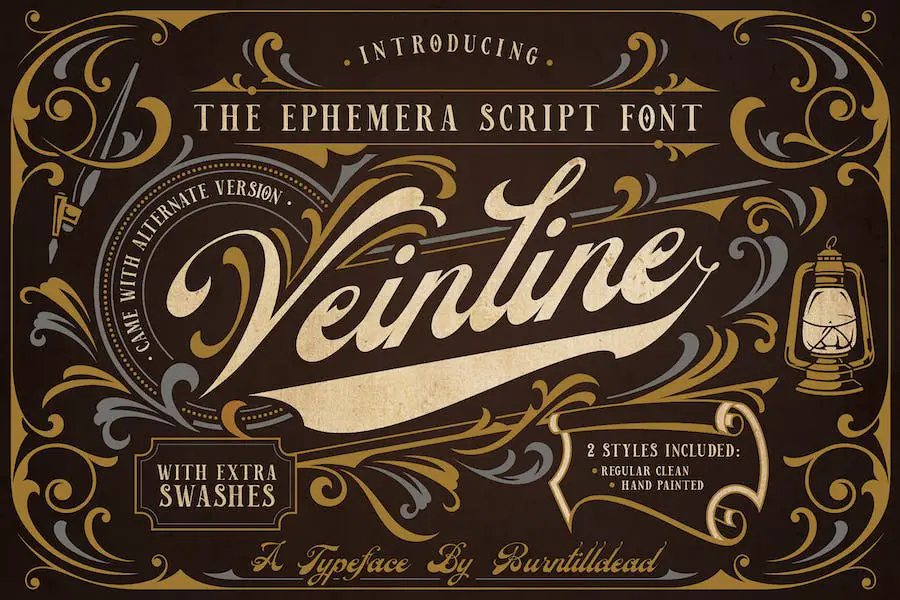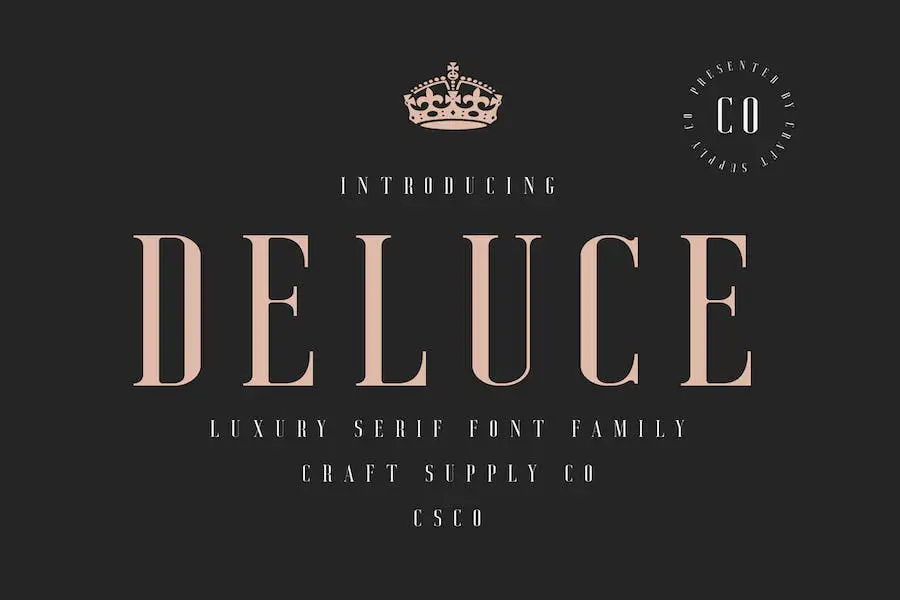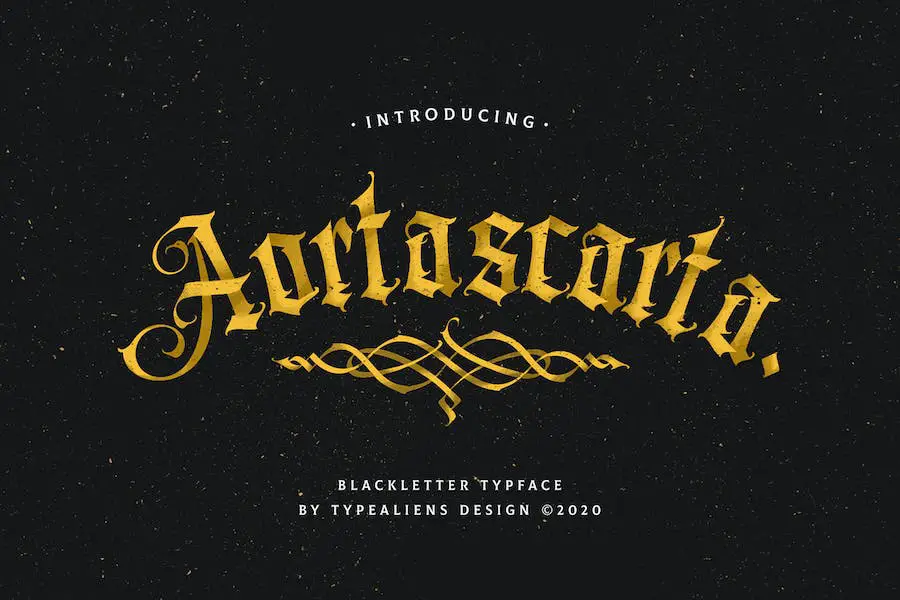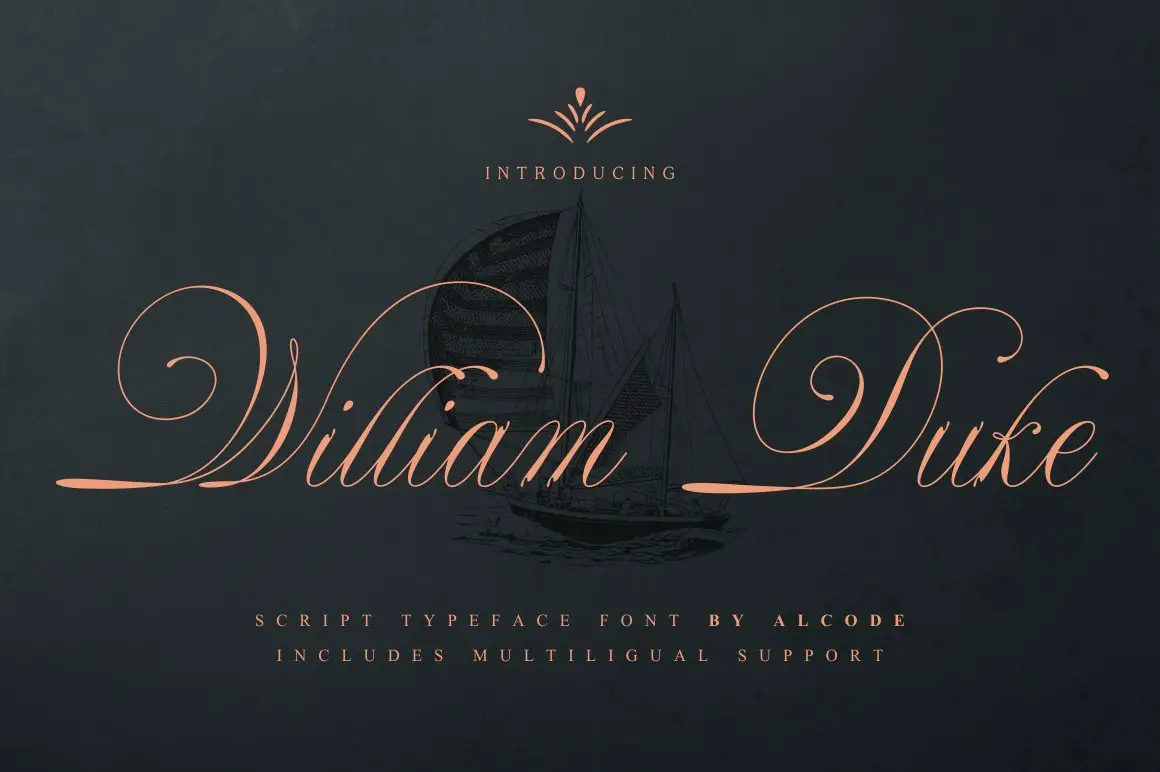
20 meilleures polices de certificat 2023 (gratuites et premium)
Publié: 2023-03-26La meilleure police pour votre certificat peut le faire ressortir même lorsqu'il est gratuit. Nous avons donc élaboré ce guide dans lequel nous vous expliquerons comment trouver les meilleures polices de certificat, quelle que soit l'option gratuite ou premium que vous choisissez.
Des polices de script aux polices sans empattement modernes, les polices de certificat sont disponibles dans une grande variété de styles et de conceptions. Il est possible de donner à votre certificat un aspect professionnel et raffiné avec une grande variété de polices de certificat.
Il est très facile de créer une impression durable avec ces polices de caractères en raison de leur équilibre entre simplicité et élégance, et elles feront ressortir votre certificat de la foule.
Cet article de blog fournira un aperçu de 21 des meilleures polices de certificats - gratuites et premium - pour vous aider à trouver le choix parfait pour votre conception. Des empattements traditionnels à la calligraphie moderne, vous trouverez toute l'inspiration dont vous avez besoin pour faire briller votre certificat. Alors, commençons!
Meilleures polices de certificat premium
BLOSTA
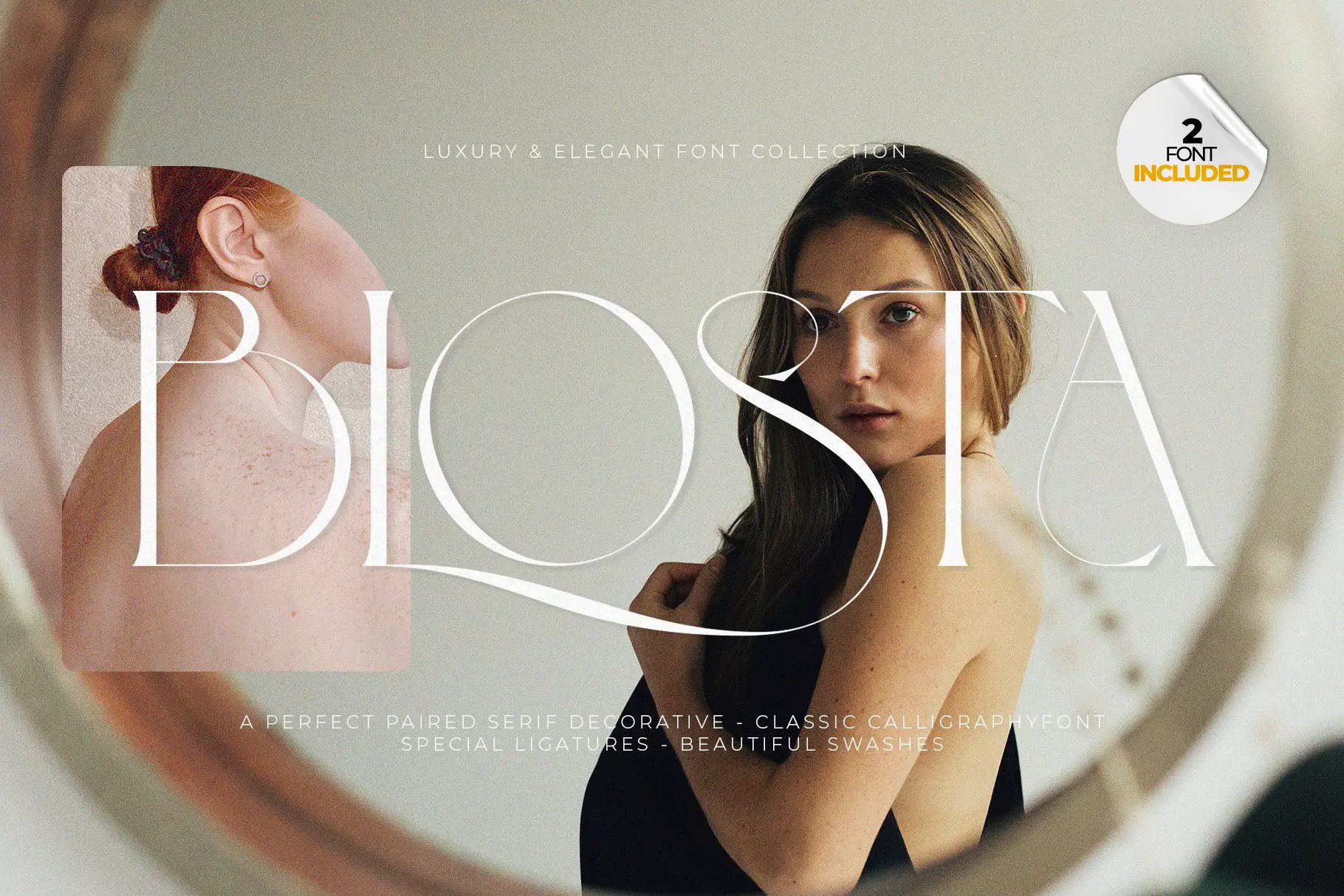
BLOSTA est une paire de polices luxueuse et élégante qui peut apporter une touche unique à tout projet de design. Avec ses deux styles différents, Serif Decorative et Calligraphy Typeface, vous pouvez créer facilement de superbes motifs tels que des supports de mariage, des couvertures de livres, des cartes de vœux, des logos, des marques, des cartes de visite et des certificats. Ses fonctionnalités OpenType le rendent facile à utiliser et à ajouter à n'importe quelle conception existante.
BLOSTA est parfait pour tous ceux qui souhaitent créer un look classique, formel ou luxueux. Que vous créiez un logo, une invitation de mariage, une carte de visite ou un certificat, BLOSTA peut vous aider à créer un beau design qui a l'air incroyable. Il a tous les bons détails pour que vos projets se démarquent vraiment et ses ligatures et caractères spéciaux donneront à votre design une touche supplémentaire d'élégance.
Qanthorely Castigra
Qanthorely Castigra est une police élégante et luxueuse parfaite pour les applications de calligraphie modernes. La police présente des courbes gracieuses et des détails complexes, ce qui lui confère une beauté intemporelle. Il est idéal pour les supports de mariage, les couvertures de livres, les cartes de vœux, les logos, les marques, les cartes de visite et les certificats.
Qanthorely Castigra se distingue des autres polices par son style unique. Ses courbes et ses angles caractéristiques sont à la fois sophistiqués et élégants, ce qui en fait le choix parfait pour tout projet de design nécessitant une touche de classe.
La police peut être utilisée pour créer des designs époustouflants qui ne manqueront pas de faire bonne impression. De plus, il est livré avec une variété de caractères et de ligatures alternatifs, offrant aux concepteurs encore plus d'options lors de la création de leurs conceptions.
Calligraphie de Mallaire
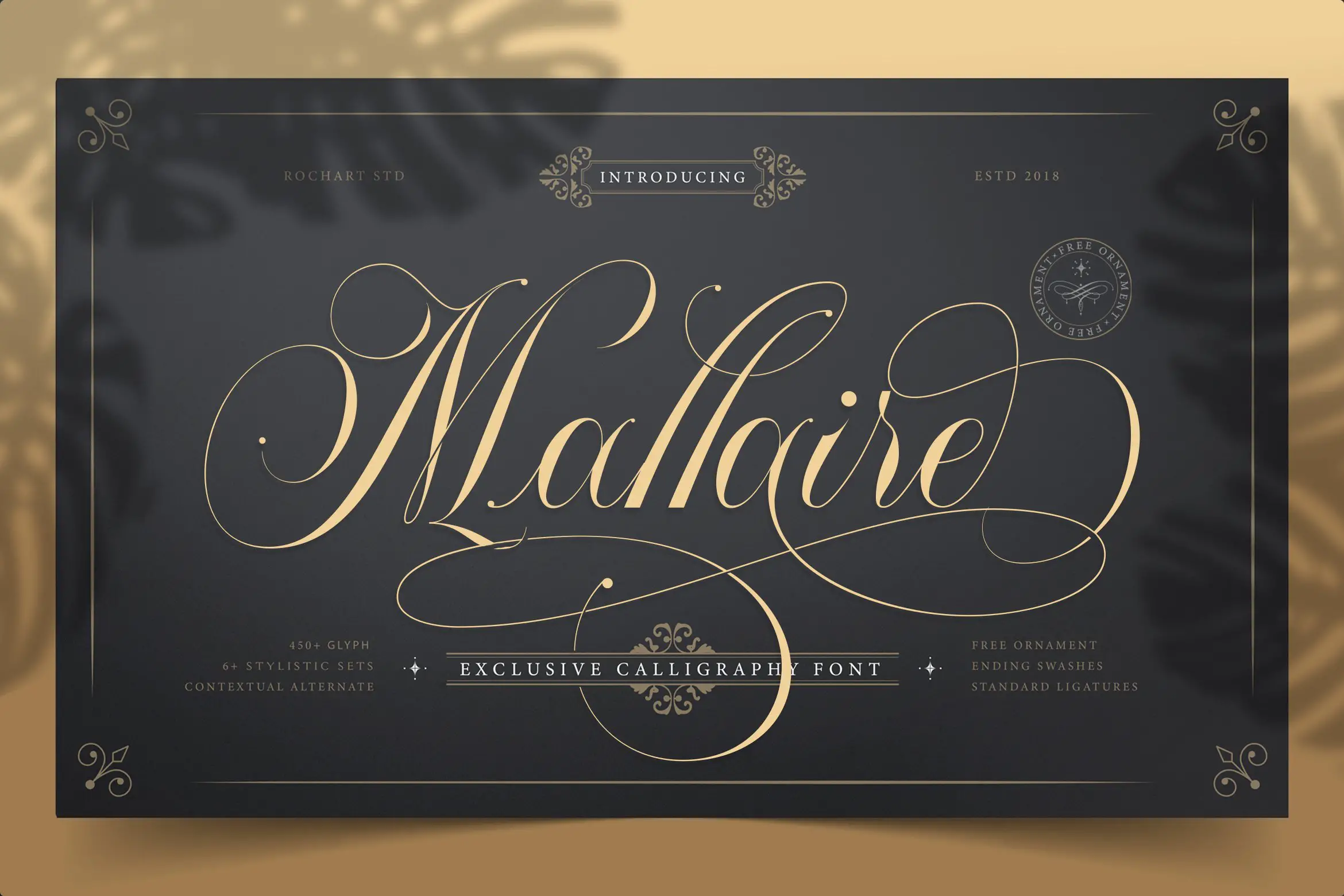
Mallaire Calligraphy est une police de calligraphie unique avec une touche classique, inspirée de l'écriture manuscrite des manuscrits anciens. Il convient parfaitement aux invitations de mariage, aux couvertures de livres, aux cartes de vœux, aux logos et à la marque, aux cartes de visite et aux certificats. Il contient des majuscules, des minuscules, des chiffres, des symboles, des signes de ponctuation et prend en charge l'encodage multilingue et PUA.
Cette police a été conçue pour fonctionner ensemble en harmonie, créant une belle esthétique qui peut améliorer n'importe quel projet de conception.
Les courbes et les swash détaillés apportent une élégance et une intemporalité aux projets, tandis que la diversité des caractères vous permet de créer de superbes arrangements typographiques. Que vous recherchiez un look formel ou luxueux, Mallaire Calligraphy est sûr d'ajouter une touche spéciale à vos créations.
JAROHY
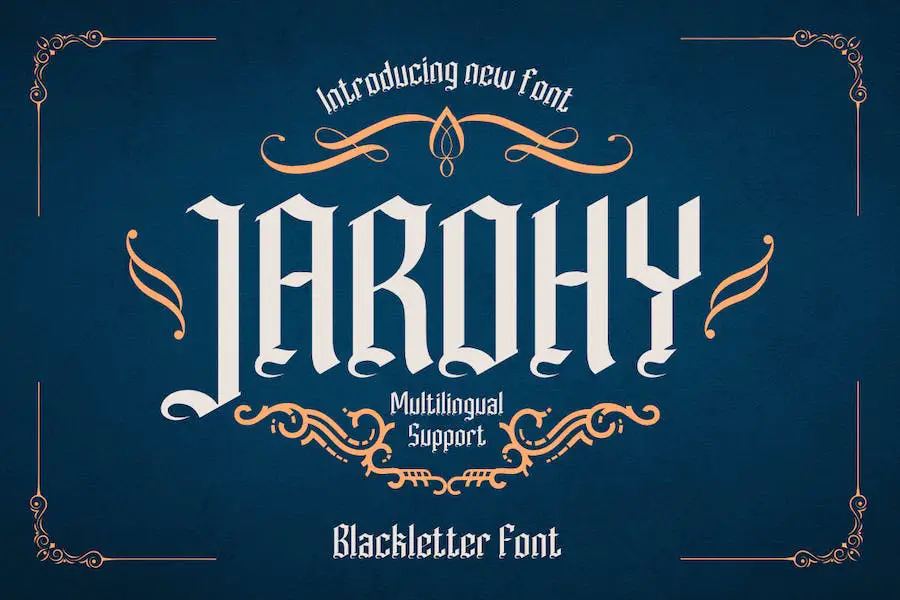
JAROHY est une police gothique parfaite pour créer des étiquettes, des designs rétro, des timbres, des badges, des affiches Oktoberfest et tout autre type de design. Il est audacieux et masculin, ce qui le rend idéal pour les conceptions qui nécessitent de la force et une impression inoubliable.
La police est livrée avec une gamme de fonctionnalités telles que sa compatibilité avec divers logiciels et plusieurs langues, ainsi que sa polyvalence pour s'adapter à différentes utilisations. Avec JAROHY, vous pouvez créer des projets de conception à partir d'étiquettes et de logos, d'en-têtes et de citations.
Si vous recherchez une police parfaite à utiliser pour votre papier à en-tête promotionnel ou professionnel, vos logos, vos conceptions de tatouage, vos cartes de visite, vos en-têtes de site Web et vos étiquettes de produits, JAROHY est votre magasin de polices unique qui vous permettra d'exprimer parfaitement ce que vous voulez .